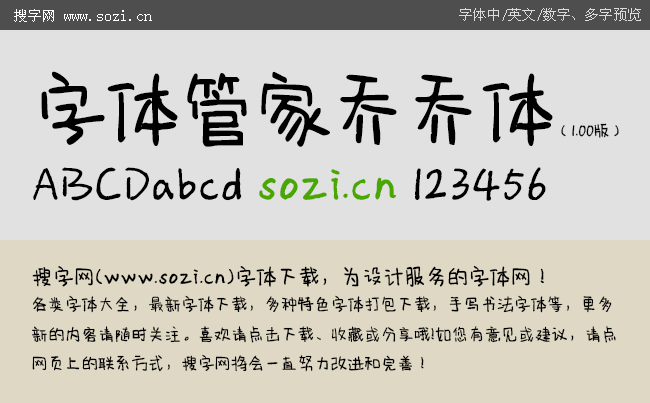
字體管家喬喬體
搜字網(wǎng)提供一款字體管家喬喬體字體下載,字體管家喬喬體是一款具有手寫(xiě)風(fēng)格的卡通字體,該字體卡通風(fēng)格十足,整體效果非常出眾,且字庫(kù)完整,可以適用于名片設(shè)計(jì)、平面設(shè)計(jì)、廣告設(shè)計(jì)、報(bào)紙雜志、電視臺(tái)廣告等領(lǐng)域使用。